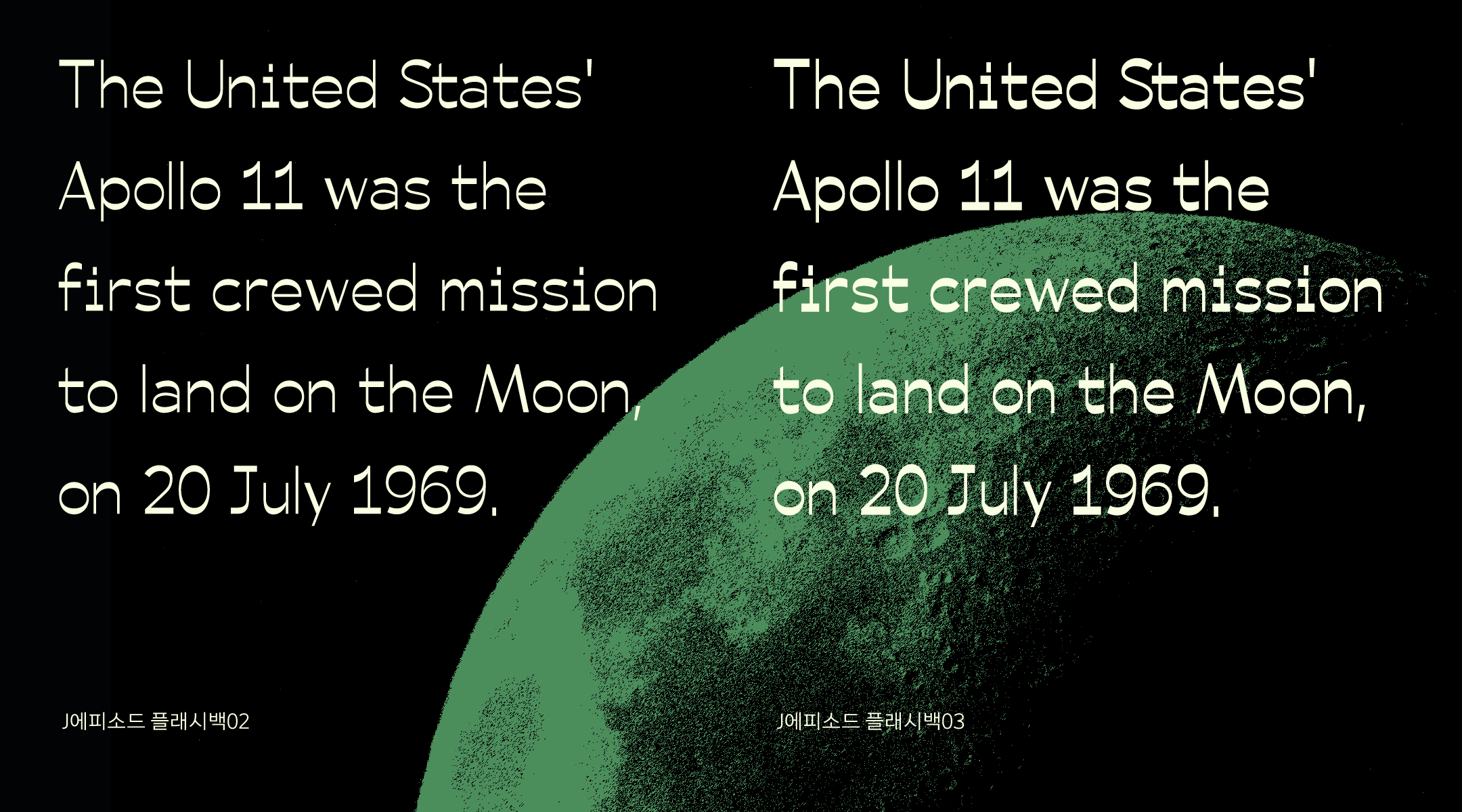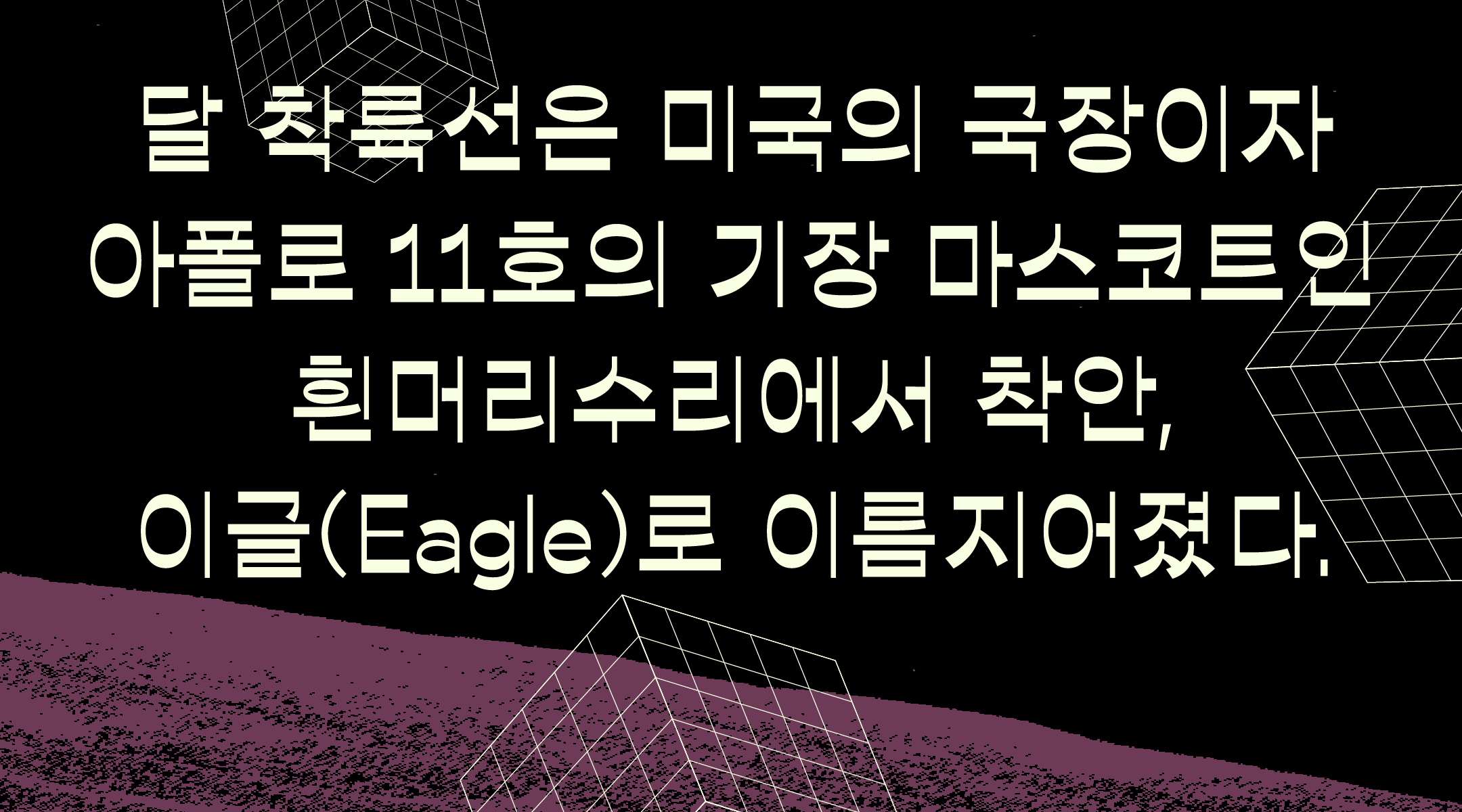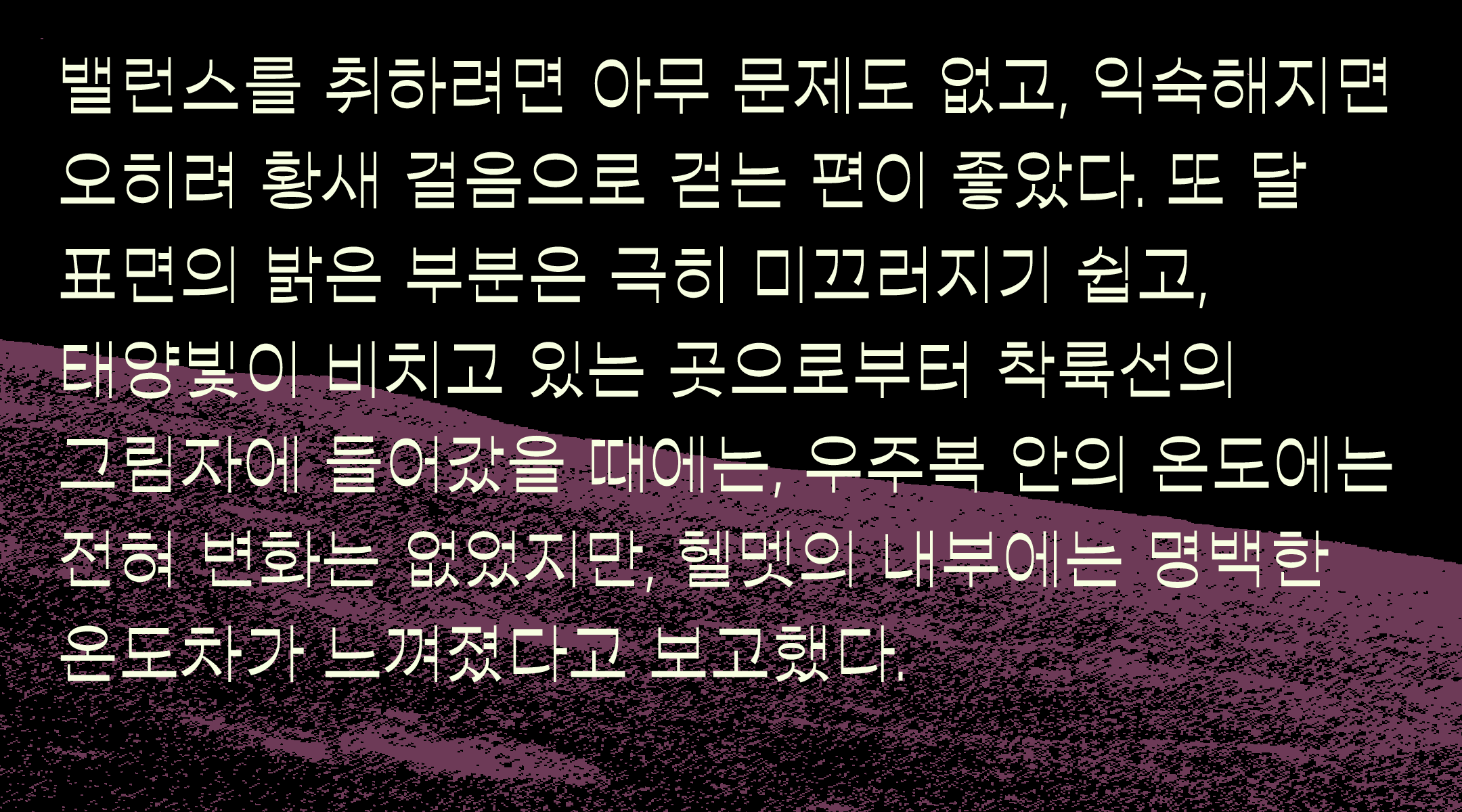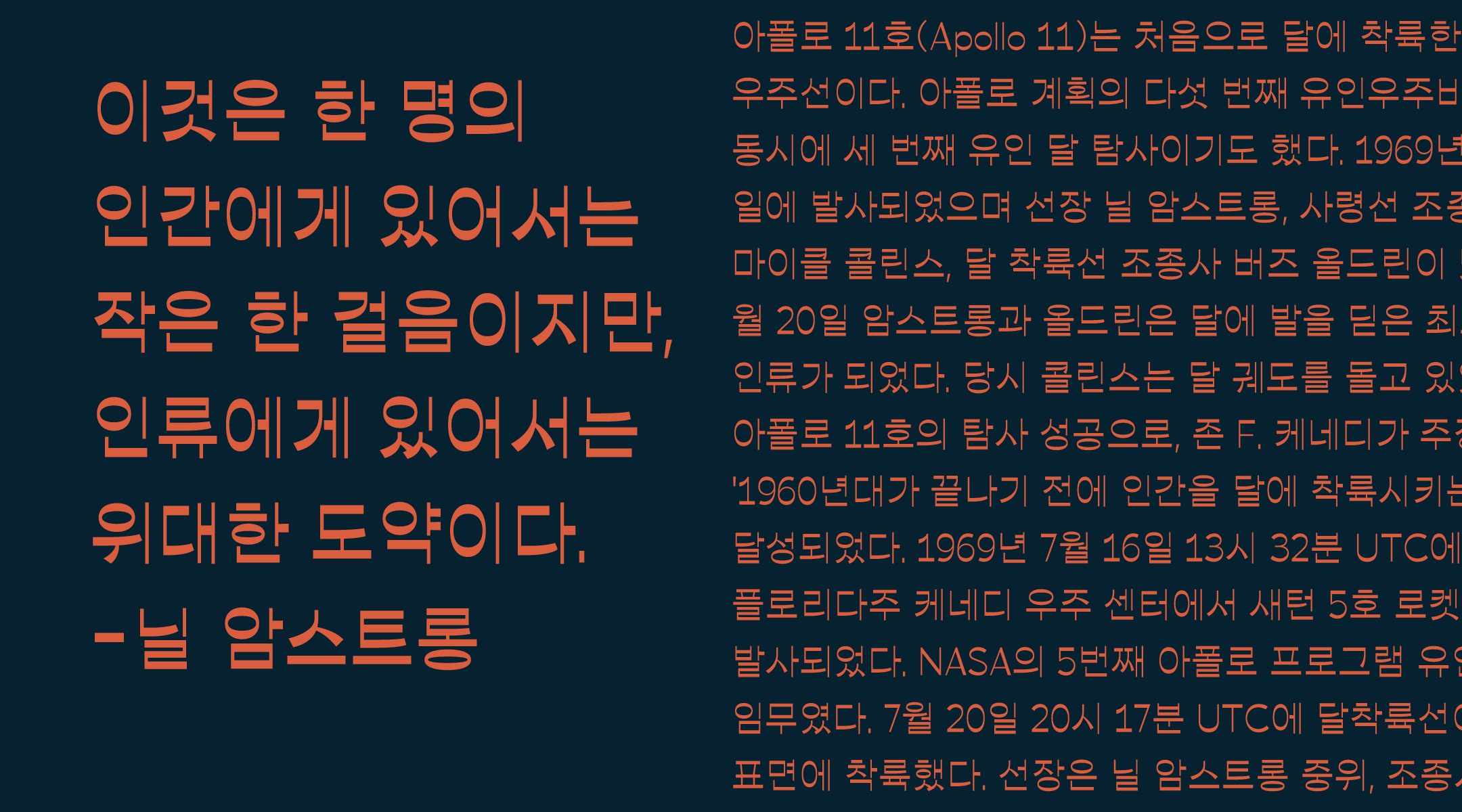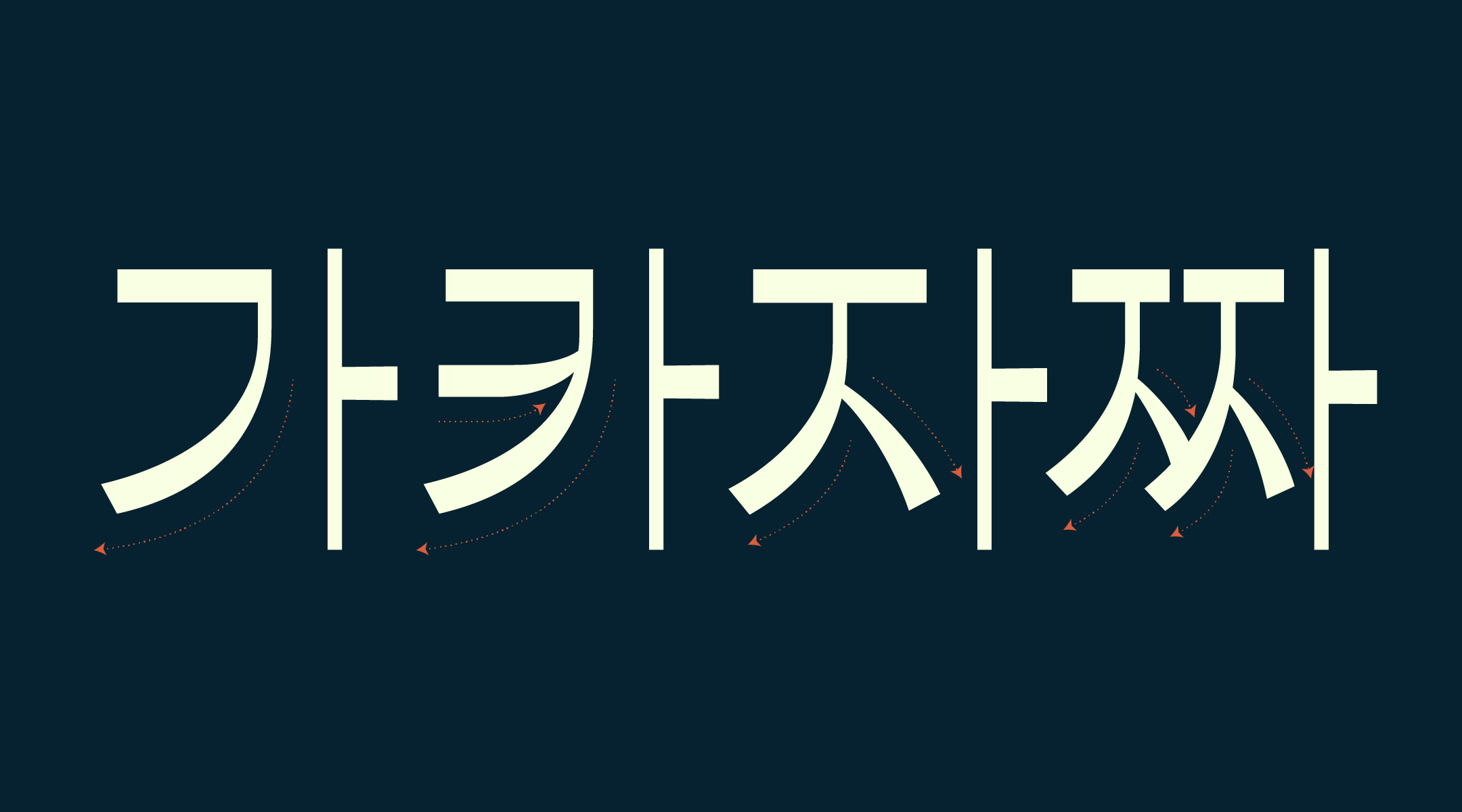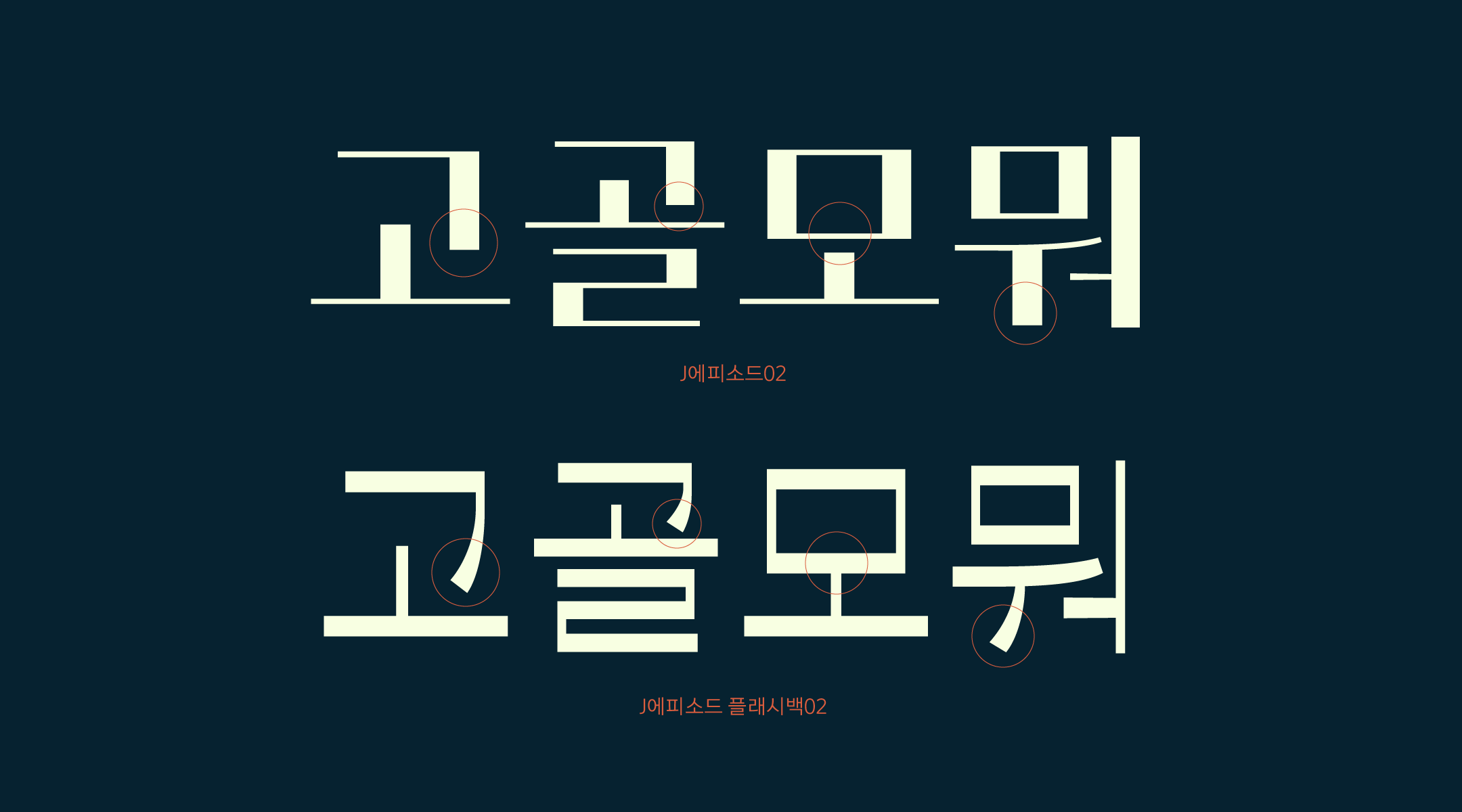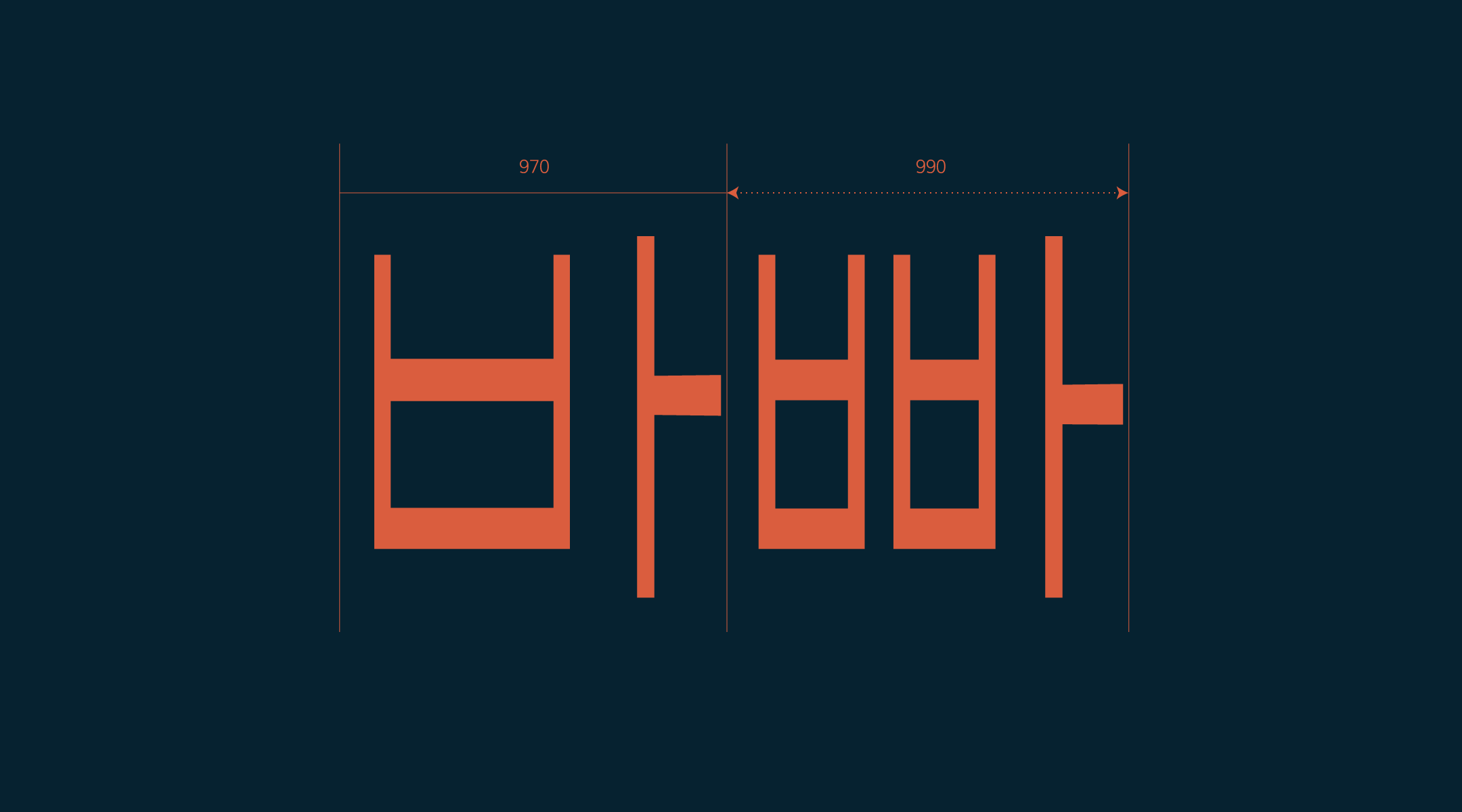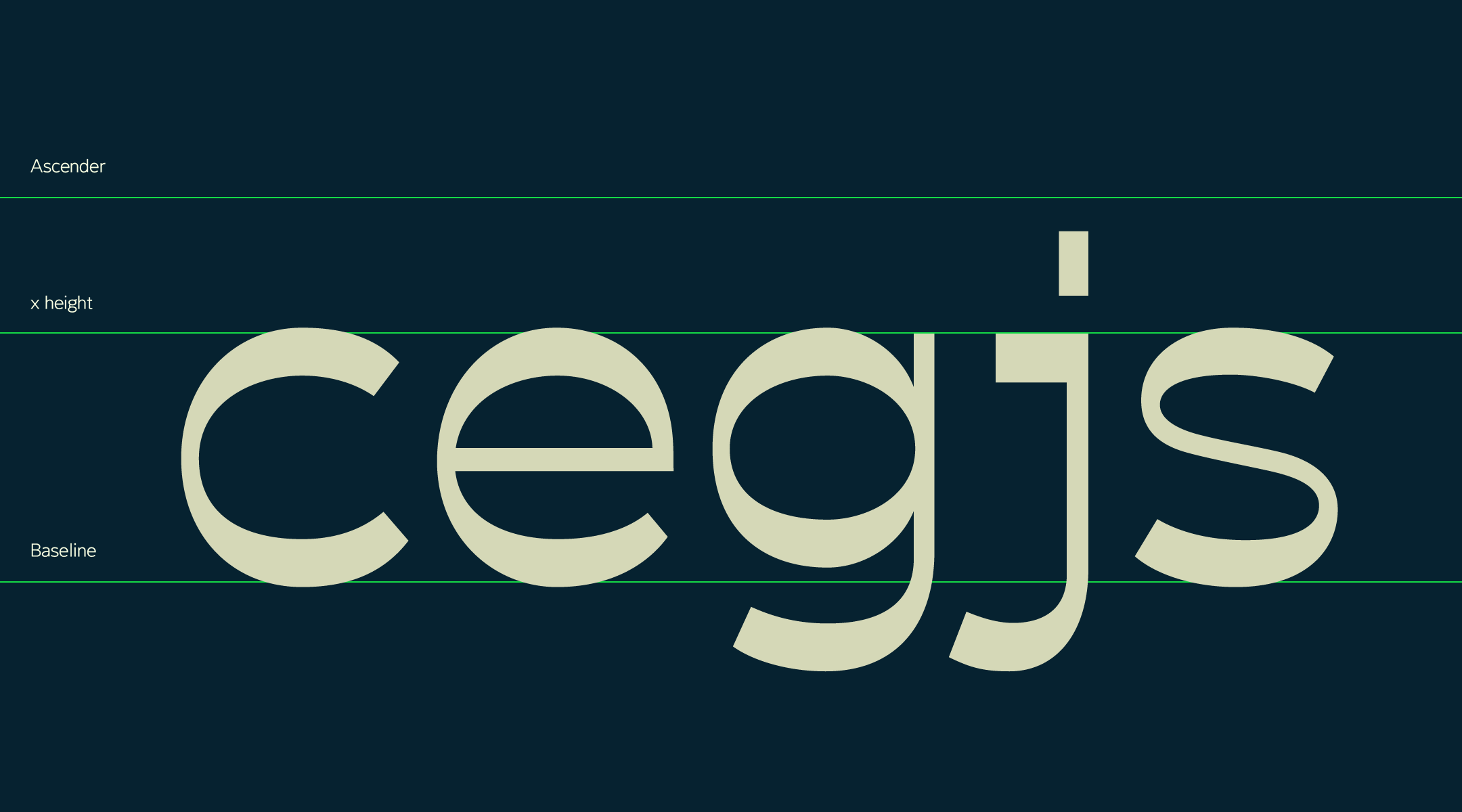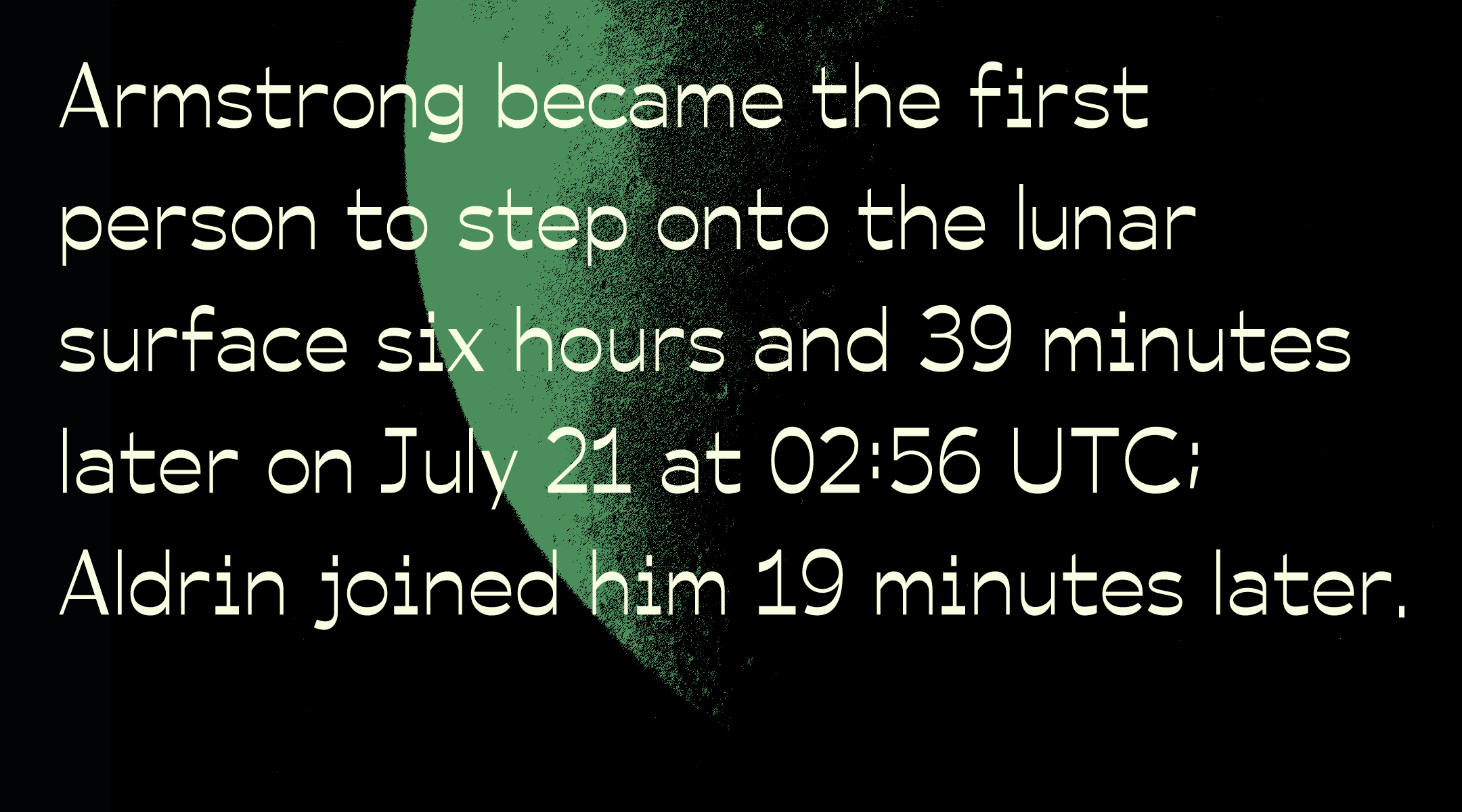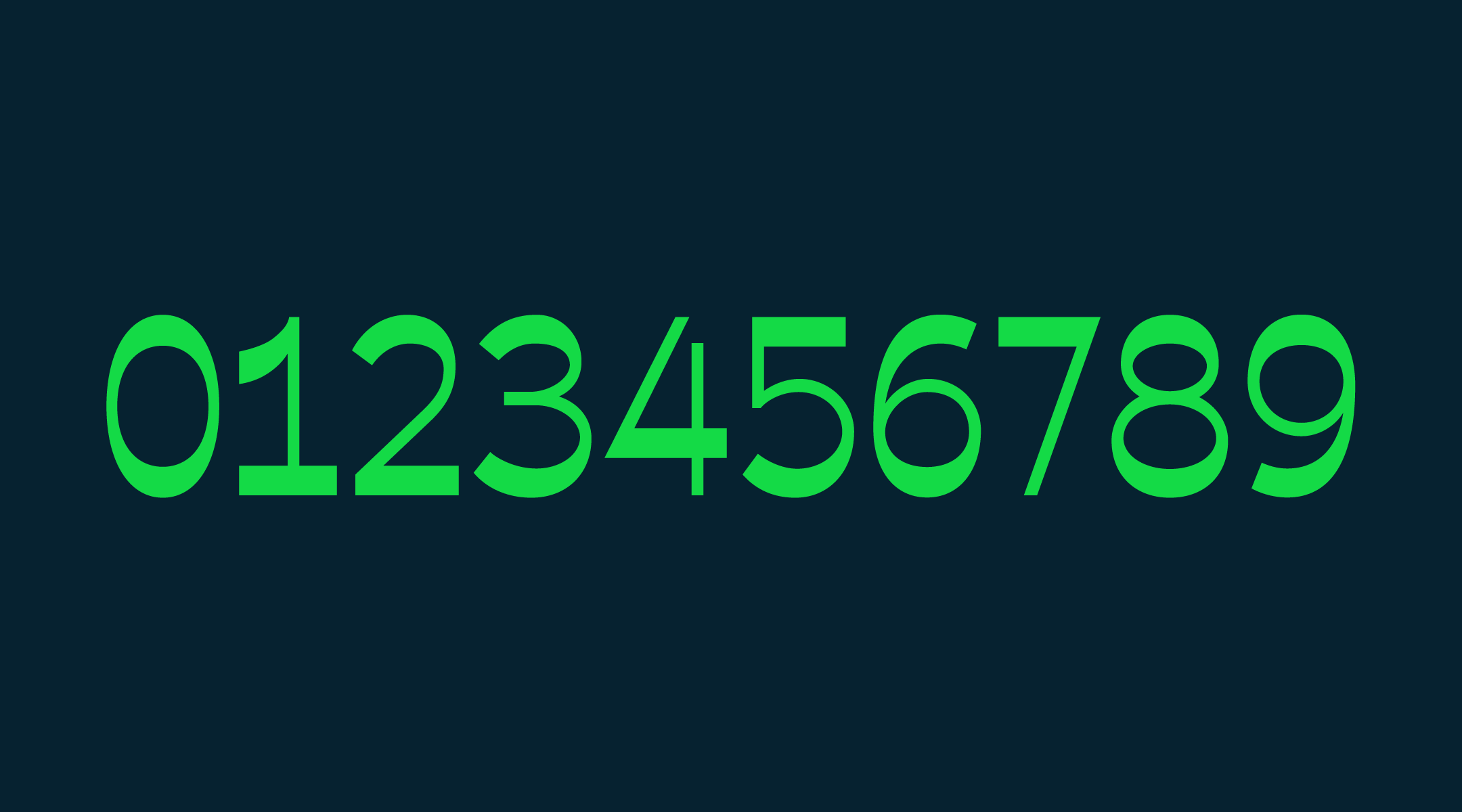
J에피소드_플래시백
다양한 컨셉으로 활용이 가능하고 독특한 디자인 요소가 많은 서체 시리즈. 개성있는 디테일로 시각적 재미를 더하고 풍부한 이야기를 담을 수 있는 서체이다.
<J에피소드_플래시백>은 J에피소드의 패밀리 폰트입니다. 2020년에 출시했던 J에피소드의 가로와 세로 획 두께 반전으로 기획했으며 새로운 패밀리의 확장을 보여줍니다. <J에피소드_플래시백> 또한 그래픽체의 계보를 따르며 동일하게 곡선과 직선의 적절한 분배를 글자 안에서 보여주지만 획 대비의 반전을 통해 상반된 인상을 보여줍니다. <J에피소드_플래시백>은 ‘과거와 맞닿은 미래’ 폰트를 지향하며 최정호 선생님의 공작체를 모티브로 참고했습니다. 레트로의 감성은 가져가되 지금 시대에서 필요로 하는 폰트에 대한 고민을 더하여 출시된 폰트입니다. 02와 03으로 총 두개의 굵기로 제작되었습니다.